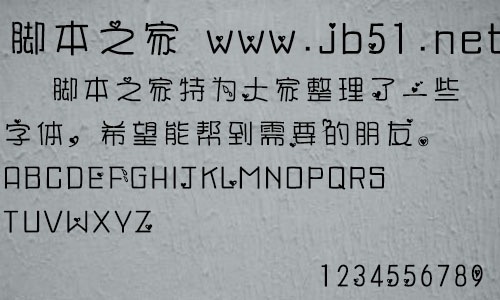
漢儀追愛體簡由漢儀字庫出品的卡通字體,字體筆觸粗細(xì)適中,字體以心形圖案進(jìn)行點(diǎn)綴,具有很好的視覺感,適合應(yīng)用于藝術(shù)設(shè)計(jì)、平面宣傳設(shè)計(jì)、網(wǎng)頁設(shè)計(jì),書法字帖等領(lǐng)域。有需要的朋友快來本站下載使用吧!